Жирний, курсив, закреслений шрифт whatsapp як поміняти, писати текст
Давай розглянемо як в Ватсапе міняти шрифт і як виділити текст жирним, курсивом або закресленим.
А також як підкреслити шрифт, перевернути текст, отзеркалить, транслетіровать і навіть передати у вигляді Абетки морзе.
Кожна сьома людина в світі активно використовує месенджер, також як і ти і, більш того, здається що все секрети і «фішки» вже знайдені. Однак вчора або вже кілька днів назад одні з твоїх знайомих надіслав тобі в незвичне повідомлення. Хочеш також?
Інструкція для Iphone і Android
Принципових відмінностей по зміні шрифту для Andoid і Iphone немає, давай розбиратися що потрібно зробити?
Не переживай, перед тим, як змінити кегель тобі не доведеться робити ніяких серйозних маніпуляцій і тому не потрібно шукати окремо інформації по заміні. Так, що на тому, що на іншому пристрої потрібно буде скористатися просто спеціальними символами.
Якими ж бувають тексти в додатку? Варто відразу обмовитися, що сильно розбігтися не вдасться, кегель адже в додатку всього чотири.
Перші три ми розглянемо трохи пізніше, а зараз давай спробуємо що-небудь написати шрифтом розробника. Його ще називають FixedSys. Його немає в настройках месенджера, однак, це нам не завадить його використовувати.
шрифт розробників
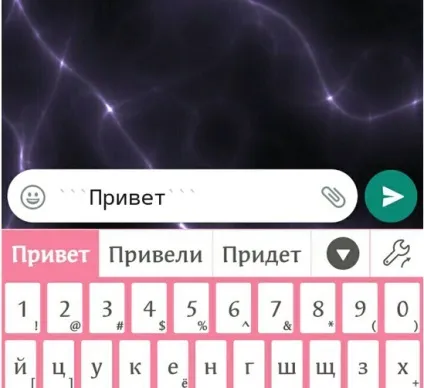
За логіе і чого? Що змінилося? А насправді все виглядає приблизно так:
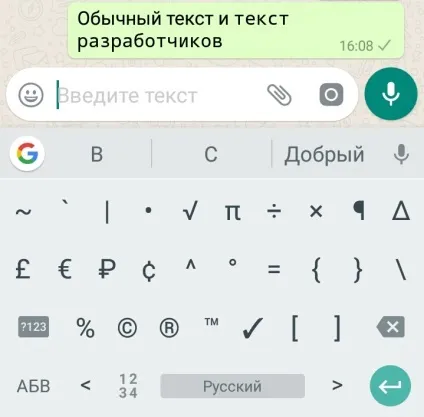
Трохи помітні відмінності!
Ми не впевнені, що розробники пишуть саме так, проте, для того щоб заінтригувати друзів в листуванні його буде більш ніж достатньо. Ну а тепер, якщо ти хочеш дізнатися інші «фішки» в Воцапе, то переходь до наступного пункту статті.
Як зробити жирний шрифт в Whatsapp
Давай розберемося як писати жирним шрифтом в Whatsapp. Для чого може знадобиться таке накреслення слів? Так для чого завгодно! Наприклад, їм можна виділити слова в тексті, які особливо для тебе важливі, або ж якщо ти злишся, підкреслити наскільки сильно ти незадоволений. У будь-якому випадку він буде вельми корисний. Інструкція:
- Відкрий чат Ватсап.
- Набери повідомлення, яке хочеш відправити.
- Додаток або частина його, яке ти хочеш виділити за допомогою жирного накреслення з двох сторін оточи точками (*). Після того як ти відправиш текст він стане жирним. Після того як в Ватсапе ти зробиш виділити жирним, текст ще в невідправленому повідомленні вже зміниться.
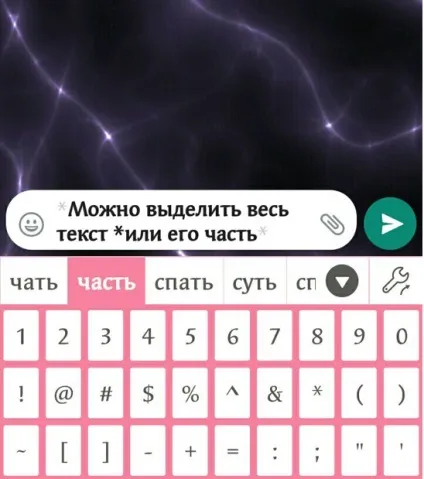
Ну ось, тепер ти розібрався як писати текст жирним шрифтом в Whatsapp - насправді все дуже просто!
Як писати курсивом в whatsapp
Для чого може знадобитися курсив? Звичайно ж, щоб написати що-небудь миле і гарне. Або ж деякі просто пишуть курсивом, т. К. Стандартне накреслення їх не дуже влаштовує. Отже, перед тим як писати курсивом в Whatsapp, переконайся, що ти відкрив потрібний чат.
- Напиши текст у вікні.
- Те слово або пропозицію, яке ти хочеш написати курсивом, щоб вилучити з двох сторін нижнім підкресленням (_).
Після всіх цих маніпуляцій у тебе вийде Italic.
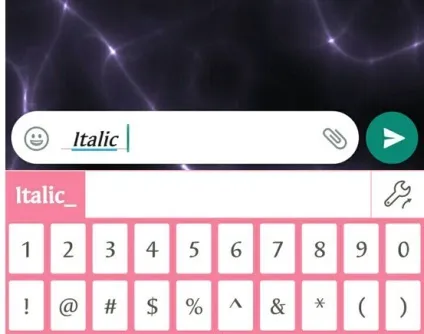
Отже, ми розібралися як писати курсивом в Вотсапе. Так само як і у випадку з жирним, курсив - це дуже просто.
Як закреслити слово в whatsapp або писати закресленим
Закреслений кегель може стане в нагоді тоді, коли ти написав щось неправильно і тобі це здалося смішним. Щоб видалити і одночасно виділити жарт можна застосувати закреслення. Також за допомогою закреслення можна акцентувати увагу на тому, що повинно було бути, але в результаті стало трохи іншим. Можна закреслити як і слово в Whatsapp, так і ціле речення.
Отже, давай розглянемо як зробити закреслений текст в Ватсапе:
- Відкрий потрібний тобі чат.
- Напиши повідомлення.
- Слово або пропозицію, яке потрібно закреслити, з двох сторін уклади в знак «тильди» (
). Після цієї маніпуляції і надіслати повідомлення, воно стане закресленим.
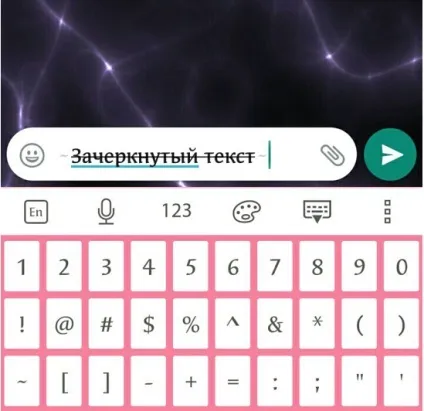
Підкреслити шрифт в Вацап
Для цього тобі потрібно зробити кілька простих кроків:
3. Вставляй в чат і відправляй;
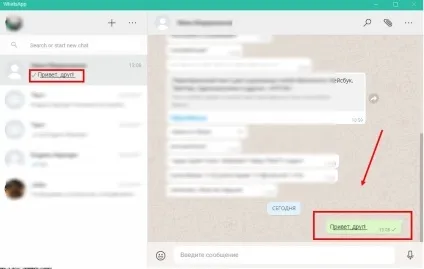
Транслетіровать текстове повідомлення в Востап
-
- Спілкуємося в чаті;
- Відкриваємо помічника по посиланню;
- Пишемо слово, пропозиції, свої думки і потім копіюємо;
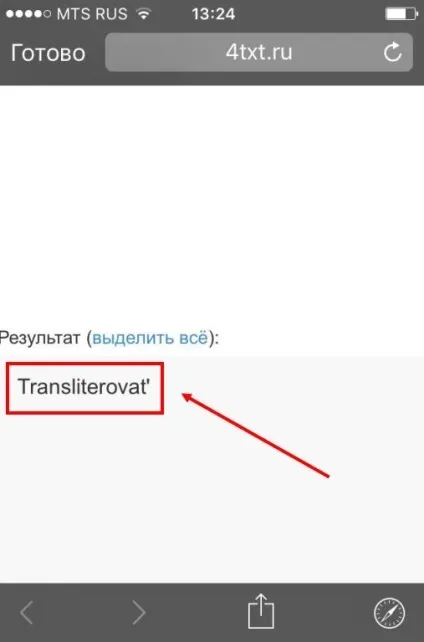
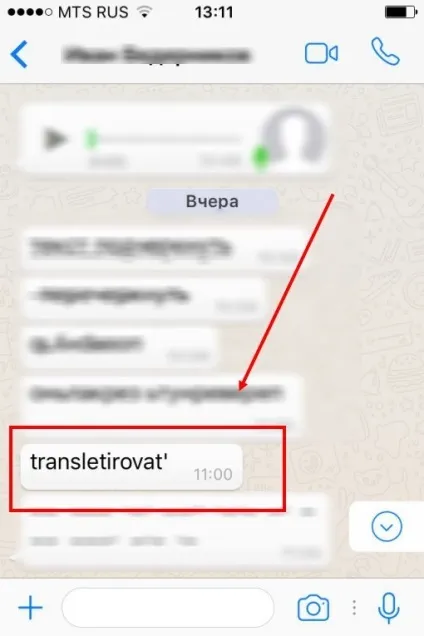
Перевернути текст в Востап
Здивуй співрозмовника перевернутим текстом, йди інструкції:
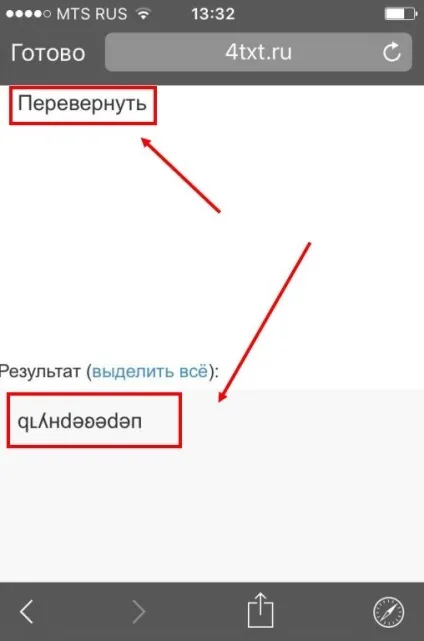
- Вставляємо в чат з листуванням;
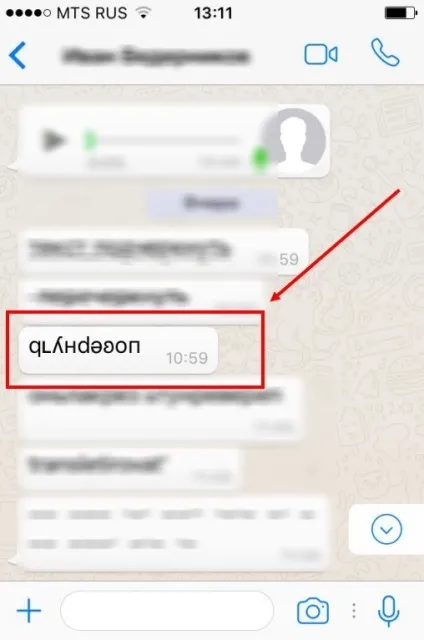
Отзеркаліть повідомлення в Whatsapp
Це перетворення не займе у тебе багато часу:
1. Заходимо на сайт нашого помічника;
2. Пишемо повідомлення, копіюємо;
3. Повертаємося до нашого діалогу. Потім відправляємо і вуаля ... твій співрозмовник бачить і не може зрозуміти, як же привернути текст;
Як зробити текст у вигляді Абетки морзе в Whatsapp?
Наостанок найцікавіше!
- Переходь до нашого сервісу за посиланням;
- Набирай повідомлення і копіюй з правої колонки;
3. відсилати один в месенджері - нехай ворожить, що ж там написано;)